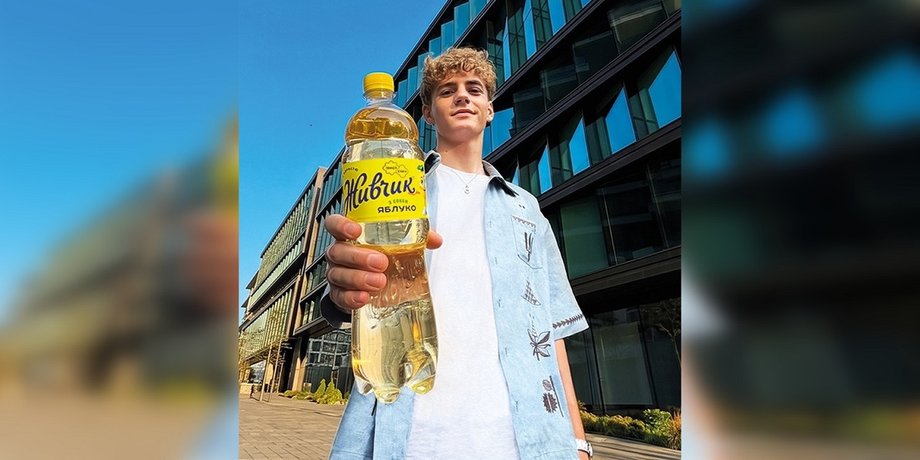
Изменят шрифты: производители "Живчика" отреагировали на скандал с российским следом
Новый дизайн "Живчика" мало кому понравился | Фото: Соцсети
Ранее бренд украинского напитка "Живчик" обновил дизайн этикетки и бутылки, что привело не только к негативной реакции на обновление, но и к обвинениям в том, что был использован шрифт, который называют российским.
О ребрендинге производитель сообщил в Threads, а после негативной реакции заявил, что шрифт будет изменен. Правда о дизайне речи не было.
В посте производитель отметил, что это первое официальное сообщение после "вашей острой реакции на обновленный дизайн этикетки": "Живчик" всегда был и остается брендом с украинскими ценностями. Любые ассоциации с государством-агрессором для нас неприемлемы. Мы последовательно поддерживаем Украину и категорически осуждаем российскую агрессию".
Бренд заявил, что дизайн еще будут переделывать
"Во время работы над дизайном был использован шрифт, предложенный партнерским агентством и официально приобретенный через международный ресурс. На этапе согласования ни со стороны агентства, ни с нашей стороны не было выявлено дополнительных контекстов, которые стали известны позже. В то же время мы понимаем, что ответственность за финальный результат лежит и на нас тоже", — заявлено в посте.
Бренд заявил, что уже принято решение изменить шрифты на упаковке и в рекламных материалах. А так как подобные ошибки являются недопустимыми, поэтому вместе с партнерами дополнительно будет усилен процесс проверки креативных материалов в будущем.
Скандал с "Живчиком" — что известно
Бренд радикально изменил дизайн этикетки на минималистичный, что вызвало возмущение у покупателей, которые призывами вернуть прежний стиль бренда, так как он для многих ассоциируется с детством.
Особое внимание пользователи уделили шрифтовому оформлению на этикетке, в частности, сходство одной из надписей с гарнитурой Road Radio. По данным, украинского веб-сервиса для покупки и аренды шрифтов Rentafont — его создала дизайнер российского происхождения под псевдонимом Glen Jan.
Обновленный дизайн "Живчика" раскритиковали и не только за русский шрифт
Досталось и агентству Brain Tank, которое работало над новым дизайном. Агентство сейчас объявило грант на редизайн в размере 50 тысяч гривен премии тому, кто предложит новый дизайн.
Агентство сейчас ищет тех, кто сделает новый дизайн